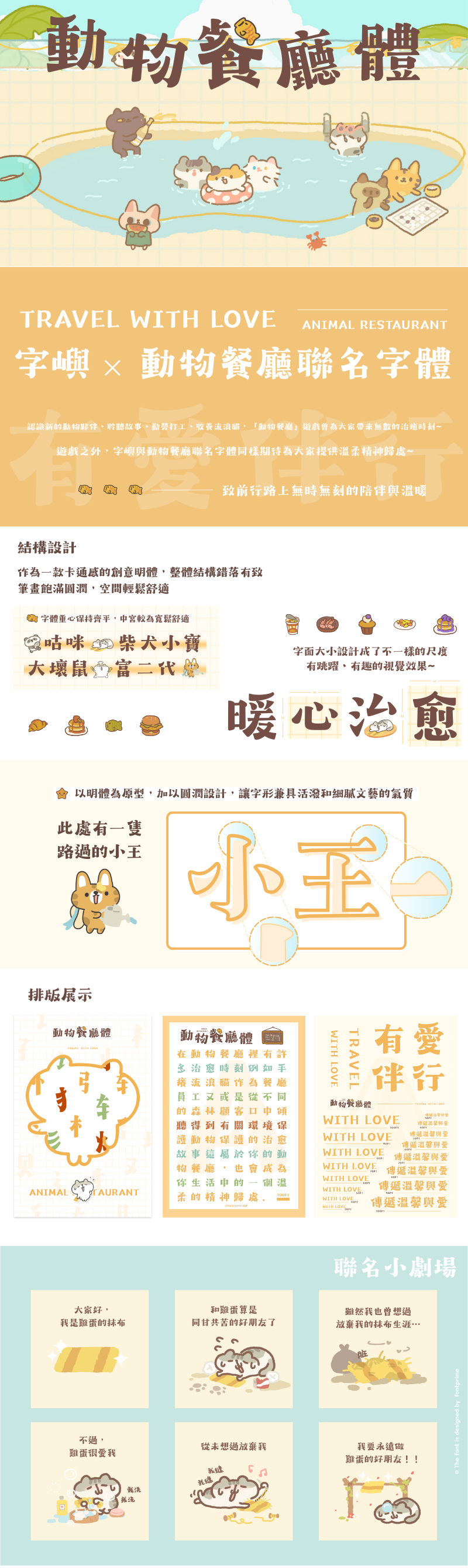
字嶼動物餐廳體
字嶼 × 動物餐廳聯名字體,治癒系創意明體伴溫暖日常 動物餐廳體以經典明體為設計原型,設計團隊將遊戲中萌系角色的圓潤特質轉化為筆畫語言,特意加入 “圓潤化” 改造:將筆畫的起筆、收筆及轉折處打磨得柔和飽滿,摒棄生硬稜角,既保留了明體字形的規整骨架,又增添了靈動活潑的質感。這種 “傳統 創意” 的融合,讓字體既能適配文藝類場景的細膩表達,又能滿足年輕化場景的活力需求,打破了人們對傳統明體 “嚴肅刻板” 的固有印象。
視覺亮點:錯落有致,打造跳躍趣味感
作為一款卡通感十足的創意明體,動物餐廳體在視覺呈現上處處藏著巧思。首先是整體結構,字體並非機械追求工整對稱,而是通過細微的結構調整,讓字形呈現出 “錯落有致” 的韻律感 —— 比如部分字體的偏旁略作偏移,部分筆畫的長短巧妙搭配,既不破壞識別性,又避免了視覺單調。其次是筆畫設計,飽滿圓潤的筆觸讓字體顯得格外 “有分量”,同時預留出合理的字內空間,使整體閱讀體驗輕鬆舒適,長時間觀看也不會產生視覺疲勞。 最令人眼前一亮的,是字面大小的差異化設計。設計師打破 “統一字面” 的常規,復刻遊戲內角色互動的靈動節奏,讓不同字符呈現出細微的尺度差異:有的字符稍顯圓潤小巧,有的則略寬舒展,搭配起來形成 “跳躍式” 的視覺效果。這種設計不僅讓文字排列更具動感,還能在排版時自然引導視線流動,無論是用於海報標題、遊戲界面,還是手賬文字、社交文案,都能瞬間抓住讀者注意力,讓內容更具吸引力。
字嶼 × 動物餐廳,傳遞陪伴與溫暖
《動物餐廳》以 “溫暖陪伴” 為核心玩法,玩家在遊戲中經營餐廳、照顧動物客人,這種治癒體驗深受喜愛,而字嶼始終致力於打造有溫度的字體設計 —— 兩者理念不謀而合,最終催生了這款 “陪伴感十足” 的聯名字體。 他們希望,這款字體不僅是 “好看的文字工具”,更能成為用戶生活中的 “溫暖夥伴”:當你用它記錄日常心情時,圓潤的字形像輕聲安慰;當你用它製作遊戲周邊文案時,卡通感與遊戲氛圍完美契合;當你用它書寫祝福語句時,細膩的筆觸能傳遞更真摯的情感。無論是工作、學習還是休閒時刻,它都能以溫柔的字形,為你提供 “無時無刻的陪伴與溫暖”。
我們希望這款字有無限的可能性:
憑藉獨特的設計與溫暖的定位,字嶼動物餐廳體的適用場景極為廣泛: 在遊戲領域,可用於《動物餐廳》及同類治癒系遊戲的界面按鈕文字、活動海報、玩家同人創作; 在日常創作中,適合手賬標題裝飾、社交平臺文案、生活 vlog 字幕,讓普通內容瞬間增添可愛文藝氣息; 在商業場景裡,能用於文創產品設計、奶茶店電子菜單、親子類品牌宣傳,吸引年輕消費群體關注。 無論是追求傳統韻味的文藝愛好者,還是喜歡可愛風格的年輕用戶,亦或是需要優質字體的設計師、商家,這款字嶼 × 動物餐廳聯名的動物餐廳體臺灣繁體字,都能滿足你的需求 —— 用一筆一劃的溫暖,為每一段文字賦予獨特的情感價值。
字元與編碼:全面實用,貼合需求
字嶼动物餐厅體 TC 擁有豐富的字元庫,以台語常用標准漢字為標准,參考jf7000字集,包括注音符號、歐文字符、阿拉伯數字和標點符號,總字符約7640字以上。涵蓋了日常生活和設計中常用的漢字、字母、數字以及各類標點符號。
無論是面向大眾的設計作品,還是涉及到國際交流、英文元素的設計專案,字嶼动物餐厅體 TC 都能提供字元支持。(目前字元集先以台語常用標準字為基礎建置,後續會逐步規劃擴充在地化用字,期待未來能更完整地服務臺語書寫需求。)在處理英文單詞或數字信息時,其字母和數字的設計與漢字相互呼應,保證了整體排版的和諧統一。豐富的字元資源讓設計師在創作過程中可以更加專注於發揮創意,靈活地運用這款字體打造出各種獨具匠心的設計作品。
字嶼動物餐廳體
已涵蓋7282個臺灣常用漢字。